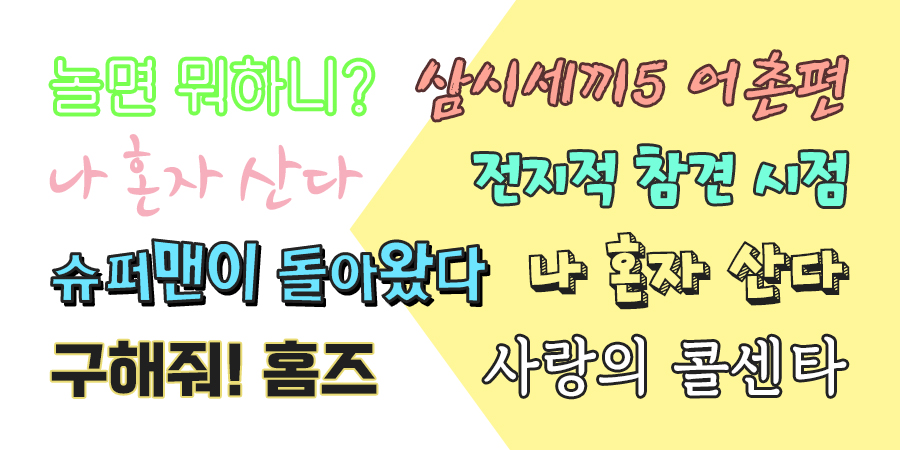
즐겨보는 예능이 있으신가요?
코로나 때문에 집에 있는 시간이 많아져서 그런지 요즘은 정말 예능 프로그램들의 전성기가 돌아온 듯해요. 예전에 비해 많이 발전한 예능만큼, 더욱 새롭고 다양해진 예능 자막들도 눈에 띄는데요~ 장면 장면을 맛깔나게 살려주는 역할을 톡톡히 하고 있는 자막에 사용된 Rix폰트들을 살펴볼게요!
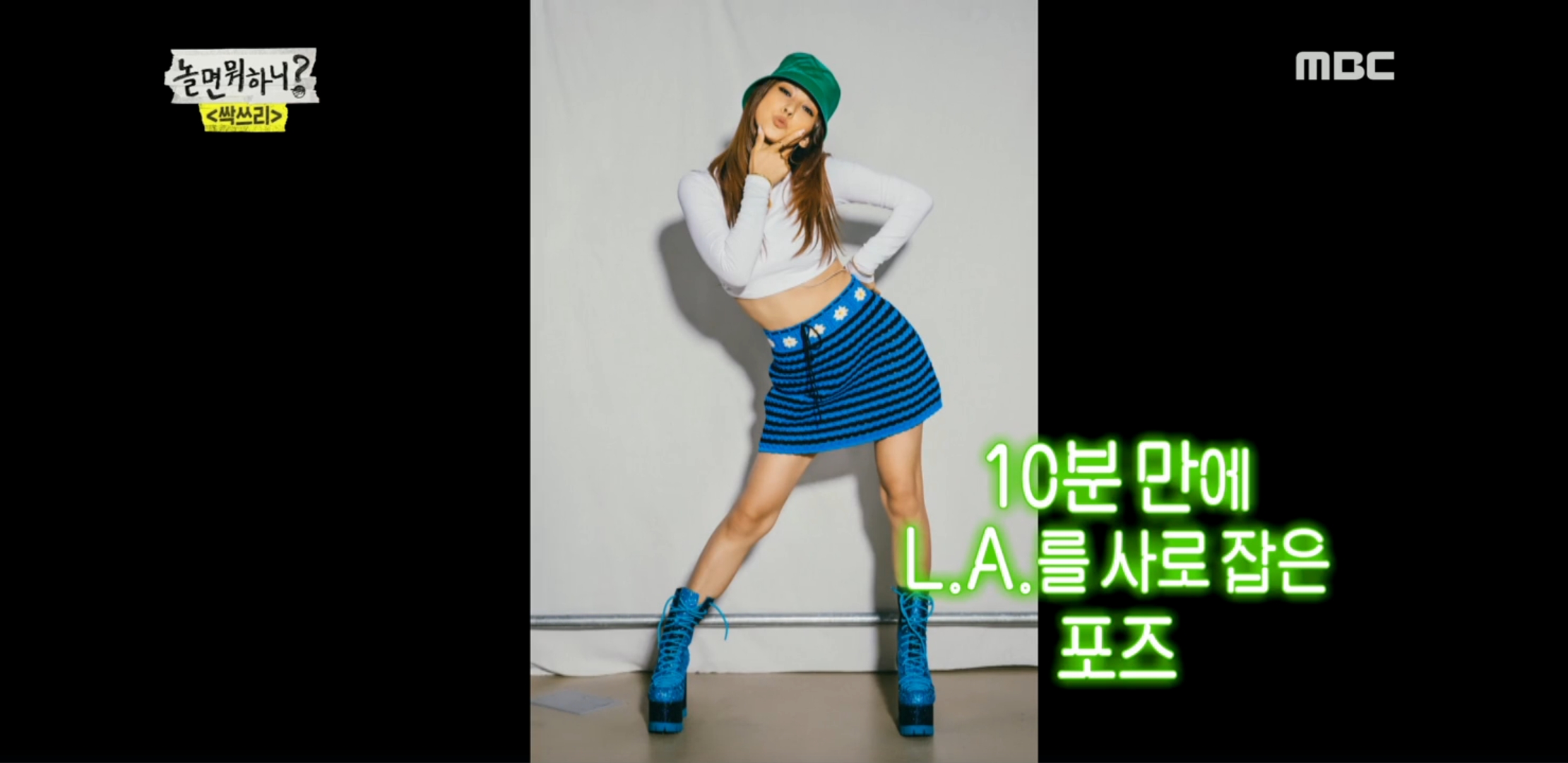
요즘 가장 핫한 그룹이죠. '놀면 뭐하니'의 싹쓰리 멤버들이 스타일링을 받았던 회차에서 이효리 씨가 포즈를 취할 때 나온 자막! 바로 Rix네온사인 폰트입니다. 서울 상경해서 물 만난 물고기마냥 반짝반짝 빛이 나는 린다G와 잘 어울리는 폰트죠~ 실제 와이어 조명처럼 획을 분리해 디자인해 폰트만으로도 실제 네온사인을 보는 듯한 느낌을 줍니다.
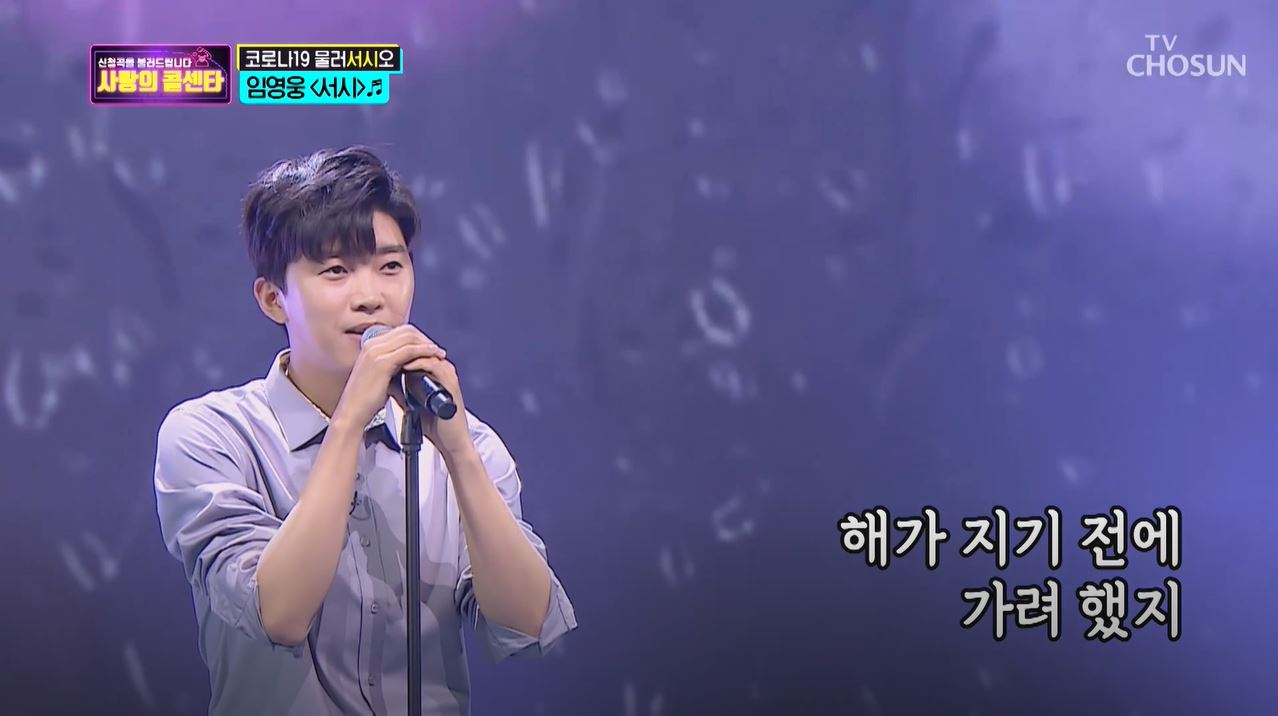
연인에게 편지를 쓰듯 정성스럽게 눌러 쓴 글씨. 손글씨 서체지만 정돈되고 단정한 느낌의 폰트로 노래 가사를 표현할 때 특히 많이 쓰여요. 편안하고 차분한 느낌을 주기 때문에 담담하게 감정을 전달하는 노랫말 자막으로 딱 어울리는 서체입니다.
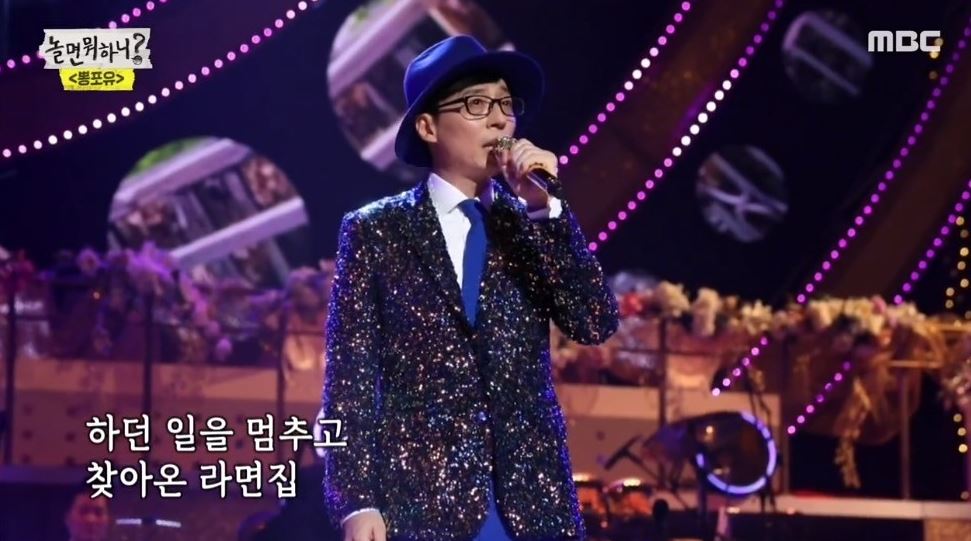
그리운 우리 산슬님!! 한창 유재석 씨가 부캐 유산슬로 활동하실 때 노래 자막으로 Rix연애일기 폰트가 나왔죠. 노래의 깊은 감동과 트로트의 진한 갬성이 잘 전달될 수 있도록 연애일기 폰트를 사용해 주셨어요~ 그나저나 표정 너무 아련보스.. 언제 또 볼 수 있는 건가요..!
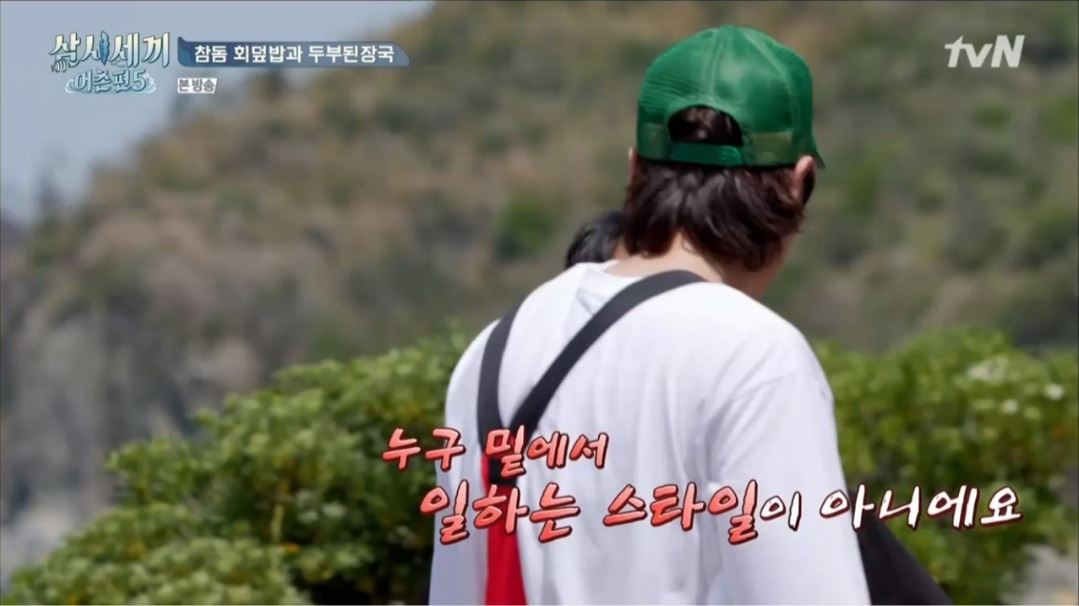
재치 있는 멘트, 빠르게 뱉어내는 멘트에 잘 맞는 Rix치타. 이름부터 뭔가 개성 있어 보이는 이 서체는 쌩-하고 달려가는 치타처럼 속도감이 느껴지는 텍스처가 인상적인 폰트입니다. '삼시세끼'에서 단호한 말을 하거나 돌발 상황에서 말이 튀어나올 때 자주 사용되는 것을 볼 수 있어요.
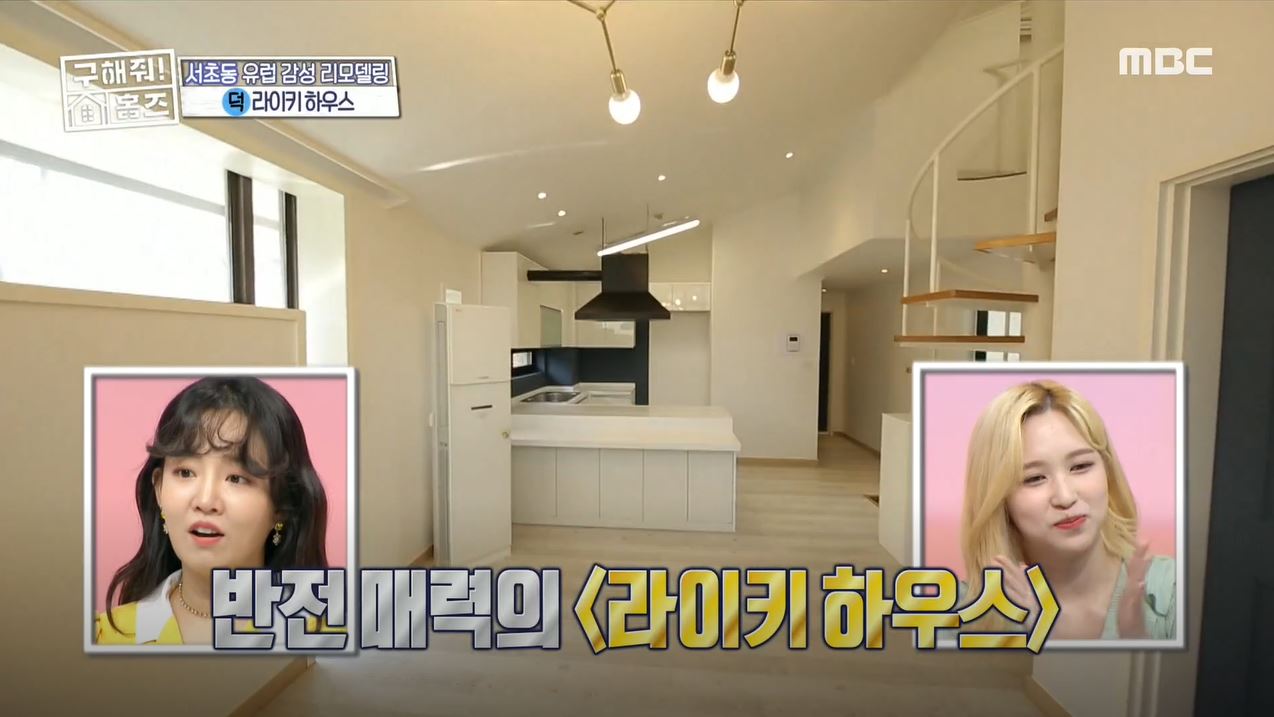
집에 대한 관심이 높아진 요즘, 스타들이 대신 집을 구해주는 예능 프로인 '구해줘 홈즈'가 단연 인기인데요~ '구해줘 홈즈'가 특히나 애정 하는 폰트! 단단하고 두꺼운 서체가 강조성이 높고, 모음의 획과 자음의 받침이 사선 처리가 되어있어 레트로적인 느낌을 주는 Rix올림픽대로 폰트입니다. 강한 임팩트를 주고 싶을 때, 힘을 실어주고 싶은 문구에 자주 쓰여요.
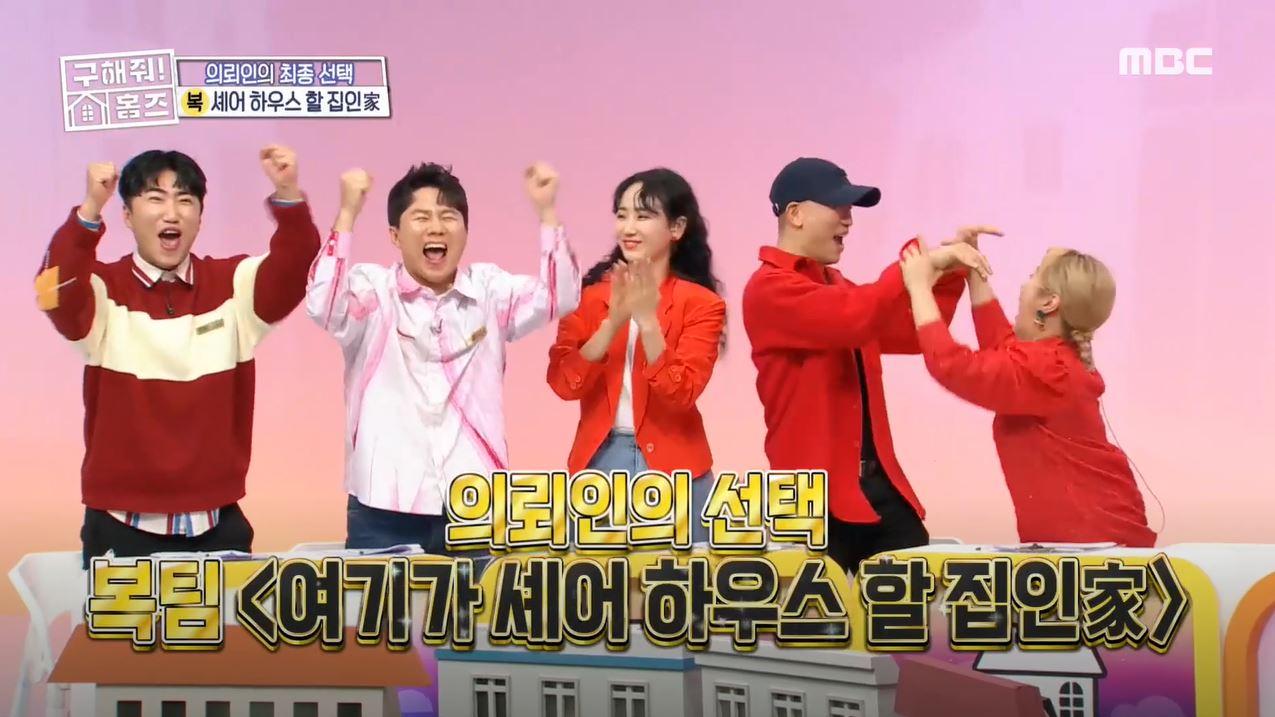
Rix부산역은 Rix올림픽대로와 비슷한 레트로 느낌이 나는 서체이지만, 부산의 광안대교 등 긴 다리를 모티브로 독특한 획의 특징을 갖고 있습니다. 기본적으로 투박하고 단단한 고딕형 구조라 주목성이 높기 때문에 방송 자막으로 많이 쓰여요! '구해줘 홈즈'에서 집 소개할 때 올림픽대로와 함께 가장 많이 쓰이는 폰트죠. 굵기 종류가 5가지나 있어 다양하게 활용하기 좋고, 특히 얇아질수록 꺾이는 부분이 더 도드라져 보여 세련되고 샤프한 인상을 줍니다.
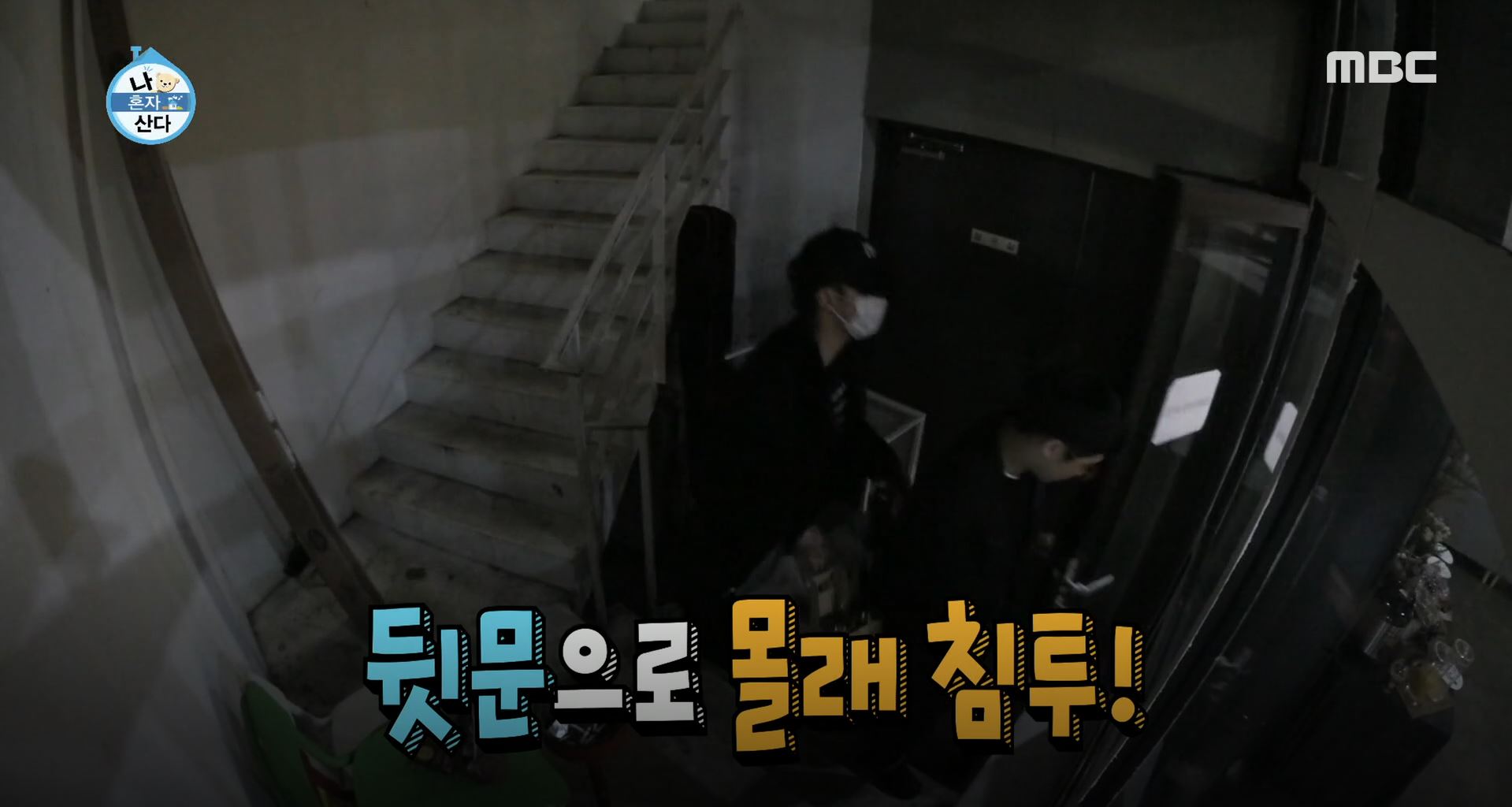
장난스러운 상황이나 재밌는 상황이 연출될 때 주로 사용되는 Rix토이그레이 폰트! 자유로운 글줄로 귀엽고도 발랄한 느낌을 주는 특징이 있어 각종 예능 프로그램에 자주 등장해요. 흥미로운 사건들이 쉴 새 없이 터지는 예능에 아주 적합한 폰트라고 할 수 있겠죠.
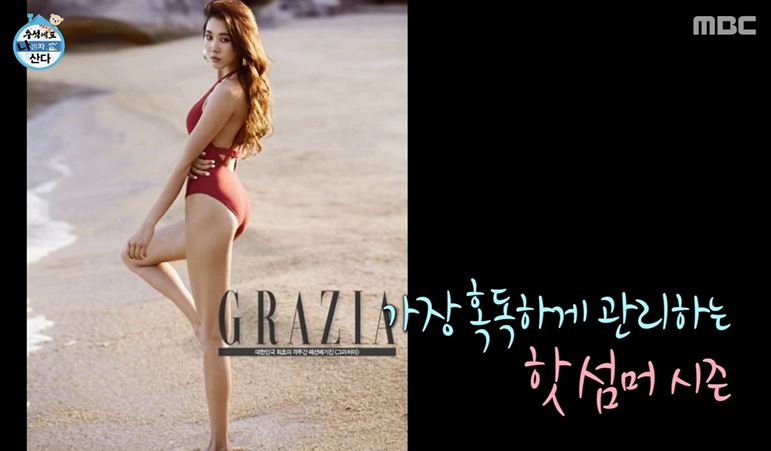
Rix가시꽃도 여러 예능에서 자주 보이는 폰트 중 하나인데요~ 특유의 손글씨 느낌과 여성스러운 스타일을 가진, 부드러우면서도 가시처럼 뾰족한 느낌을 표현한 서체입니다. 가벼우면서 세련된 폰트로 영상과의 어우러짐이 자연스러워 방송 자막으로 굉장히 활용도가 높습니다.
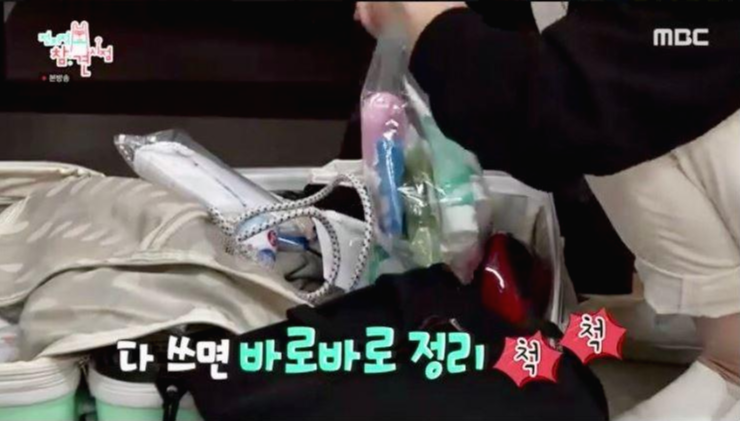
핫한 예능 중 하나인 '전참시'에 등장한 Rix가로수길 폰트. 리드미컬하게 움직이는 듯한 글씨가 어떤 행동을 표현할 때 쓰기에 적당합니다. 다른 글씨체와의 조합도 자연스러워 예능 방송 자막으로 최적화된 폰트예요!
귀여운 아이들의 솔직한 이야기를 들을 수 있는 '슈퍼맨이 돌아왔다'에서도 자주 보이는 Rix가로수길. 두꺼운 글씨와 통통 튀는 리듬감을 갖고 있어 사랑스러운 개구쟁이 친구들의 멘트와 찰떡쿵!
두둥! 뭔가 대단한 일이 벌어질 것만 같은 폰트 Rix개봉박두. 글꼴이 커졌다, 작아졌다, 기울었다 아주 자유분방합니다. 박진감 넘치는 액션 영화를 연상시키며, 글자의 크기에 강약을 주어 마치 효과음처럼 강조되는 느낌을 줍니다. 그렇다 보니 이런 방송 자막에는 물론 TV광고나 유튜브 등 다양한 영상에 사용되고 있습니다.
강조성이 높은 단단한 고딕형 폰트부터 개성 있고 독특한 손글씨 폰트까지. 수많은 예능 프로그램에 등장한 Rix폰트를 살펴봤는데요~ 잘 몰랐던 숨은 보석같은 폰트들도 참 많죠ღ'ᴗ'ღ
요즘은 예능도 유튜브로 알짜배기 부분만 모아서 보는, 일명 '짤'로 보는 시대입니다. 1인 미디어의 시대라고 해도 과언이 아닐 정도로 스마트폰 하나만으로도 쉽게 콘텐츠를 만들고 공유할 수 있는 플랫폼이 주를 이루고 있고요. 직장인도, 프리랜서도, 아이를 키우는 젊은 맘들도 모두 미디어에 뛰어들고 있죠. 그만큼 폰트가 필요한 곳이 점점 많아지고 훨씬 다양해지고 있습니다.